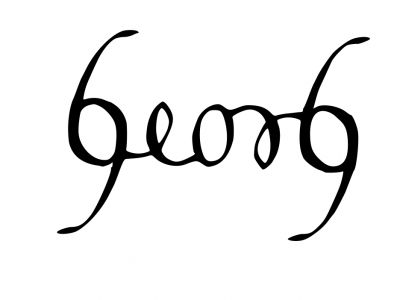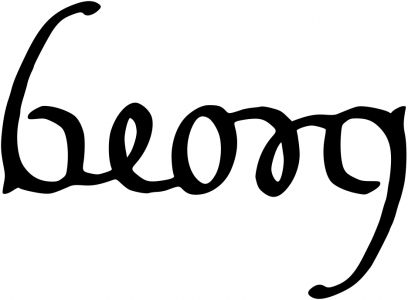
Im Zuge des Da-Vinci-Code-Films sind zur Zeit Ambigramme ja mal wieder ganz hoch im Kurs. Erfreut habe ich dabei festgestellt, dass sich mein Name – das heißt: unser Name, verehrter Kollege Bleisetzer – geradezu hervorragend für ein Ambigramm eignet: 575_georg2b_1.jpg
So, wenn jetzt alle Laptopnutzer bitte einmal das Gerät in die Hand nehmen und um 180° drehen, bitte. Die Desktopnutzer können ihre Vorstellungskraft bemühen oder in den Kopfstand gehen :-)
Gruß, Georg
Warum hab ich das nicht gleich gesehen, das G/g muss ja gar nicht symmetrisch sein:575_georg3a_1.jpg
Da gibt man sich Mühe – und keiner klopft einem auf die Schulter. Also, bevor der Thread unwiderruflich wieder verschwindet: saubere Sache! Ich finds ja nicht so faszinierend, hatte aber vor einiger Zeit mit einem italienischen Kollegen zu tun, der quasi hauptberuflich solche Vorlagen (v. a. für Tätowierungen) herstellt …
Niklaus: Nicht, daß es mich etwas anginge, aber in was für Kreisen verkehrst Du eigentlich? :)
Ich muß gestehen: Ich kannte den Begriff Ambigramme zuvor gar nicht.
Ja, der Georg. Macht schon was her..
Besten Dank. Hat mir Spaß gemacht.
… in ganz anderen – und Tätowierungen mag ich (nüchterne "Schweizer Schule"!) eigentlich überhaupt nicht. Das war eigentlich ganz ein netter (Graphiker-)Kollege, einfach mit zunehmendem Einschlag ins Herr-der-Ringe-Fantasy-Keltisch-Tribal-Ambigrammatische.
versteh ich, hab damit auch nicht viel anfangen können damit, bis zu Dan Browns Buch Illuminati (Angels & Demons). Da gehts um böse Machenschaften im Vatikan, die mit Ambigrammen zu tun haben. Und letztere wurden im Buch von John Langdon verfasst. Yepp, den gibts wirklich. Ein anbetungswürdiger Typ, der Unglaubliches in der Gestaltung und Neufassung von Lettern macht. Und, ja, der Titelheld in einigen Büchern, also auch im Da Vinci-Code heißt Harry Langdon, den der der Tom Hanks spielt.
Website anschauen, ist Pflicht.
Eines meiner Lieblingslogos ist das für das neue Fahrrad seiner Tochter (Jessica Taft Langdon):
EDIT: Hoppla, im unredigiertenPosting habe ich den Da Vinci Code mit Illuminati verwechselt.
Ich finds ja nicht so faszinierend …
Ach ja, ich hab inzwischen auch festgestellt, dass man aus fast jedem Namen mit etwas Geduld ein Ambigramm machen kann – aber bei kaum einem so leicht wie bei Georg :-)
Georgs sind halt unveränderlich - Du kannst sie drehen und wenden wie Du willst - Qualität bleibt Qualität.
Gut, dass John Langdon Sachen wie «Aerosmith» ‹ambigrammieren› kann, das ist schon hohe Kunst. Aber ich seh’s mir an, denke «nett» – während der Gestalter mir wohl etwas von Da-Vinci-Code, Rückwärtscodes und magischen Symmetrie-Mandalas erklären würde. Da habe ich doch mehr Freude an einem schön gestalteten Buch.
... ich hab mir die Seite auch angesehen - und auch die "anleitung" von mr langdon - da ist er gar nicht so verbissen "magisch", sondern stellt es eher als eine grafische spielerei dar (nicht jeder hat so einen - sagen wir mal vorsichtig - tick wie dan brown - und nicht jeder wird damit so reich).
aber niklaus hat recht: das ist alles sehr schön und bewundernswert, aber hat in etwa den nutzwert wie sudokus zu lösen. wenn man mal vom tätowieren absieht ...
"das ist alles sehr schön und bewundernswert, aber hat in etwa den nutzwert wie sudokus zu lösen. wenn man mal vom tätowieren absieht ... "
Gut, aber dann zwingt sich mir im Reflex die Frage auf (und die ist bitte wirklich als konkrete Frage zu verstehen):
Muß denn wirklich alles einen Nutzwert haben?
Und falls ja: Woran orientiert man sich bei der Festlegung eines solchen Nutzwertes? Rein materiell?
Genau so wird es ja in unserer anglo-amerikanisch geprägten Gesellschaft definiert. Und sickert in eines jeden Gedanken ein. Was zur Folge hat, daß wir uns alle auf unterschiedlichen Ebenen und vielen Parallel-"Märkten" nur noch um Gewinn-Maximierung bemühen.
Provokant formuliert, kann ich unterstellen, daß auch die zitierte Frage letztendlich auf dem Prinzip einer solchen Gewinn-Maximierung beruht.
Ich sehe viel mehr Sinn darin, auch einmal etwas (vom Prinzip der Gewinn-Maximierung her gedacht) völlig sinn-entleertes lerne bzw. mich damit beschäftige. Mit dem Ziel, in dieser Beschäftigung an sich Befriedigung zu finden. Ob das Ergebnis dann einen "Nutzwert" hat, ist mir nicht nur gleichgültig, sondern empfände ich als kontra-produktiv im Sinne meiner Absicht.
Nur gut, daß ich nichts über die Tagesmeinungen von Claude Garamond weiß ...
Eben: Interessant fand ich, wie die Meinungen der doch zumeist Profis – und zwar die ästhetischen Urteile! – sich sofort verschärften, als der Betreffende seine politische Einstellung vermehrt kundtat.